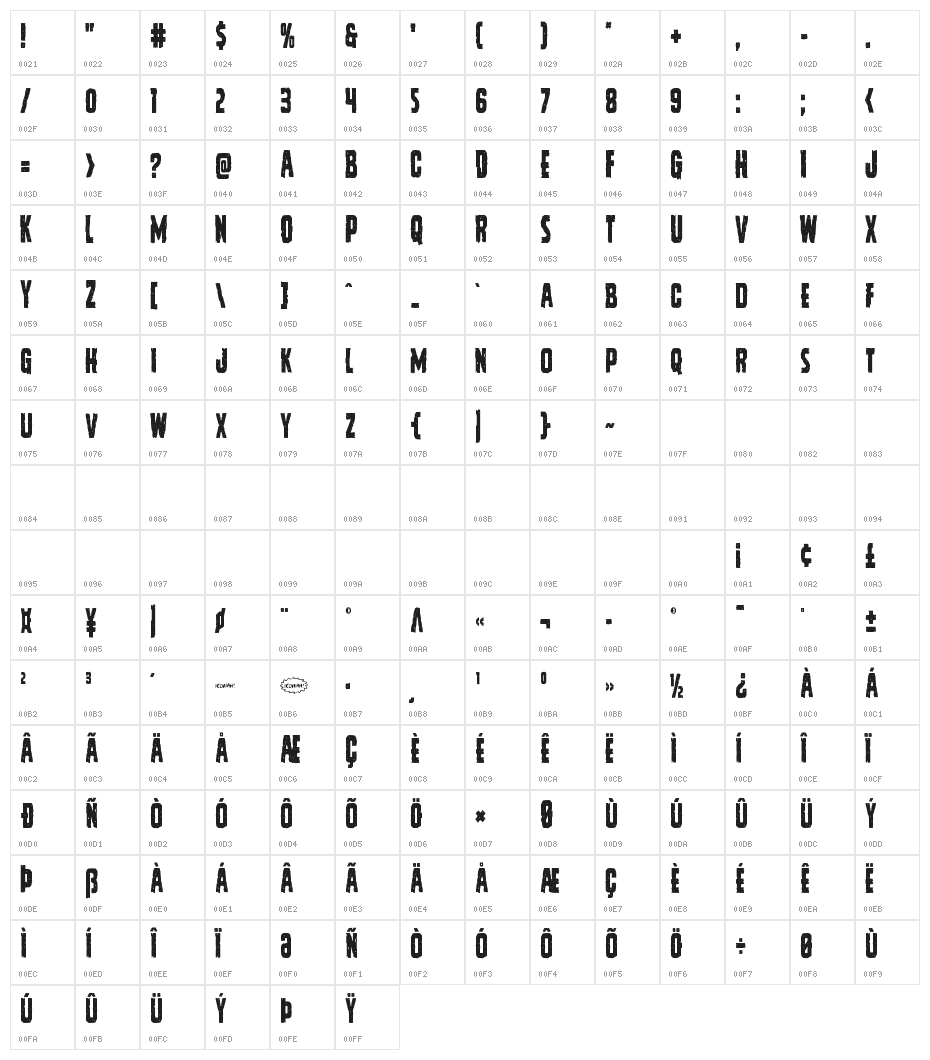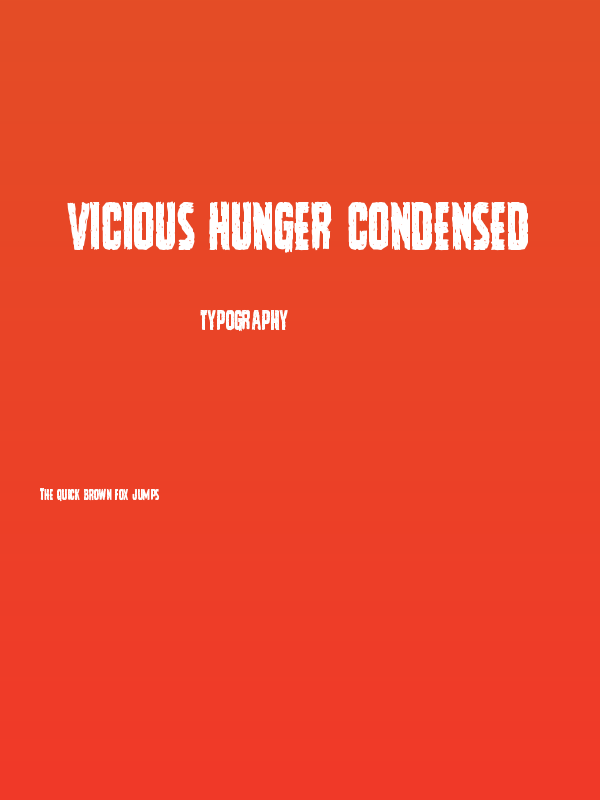
Vicious Hunger Condensed Font
✎ Messy
| Vorgeschlagene Projekte | Ideal for posters, album covers, branding for edgy products, and any design needing a bold, gritty look. |